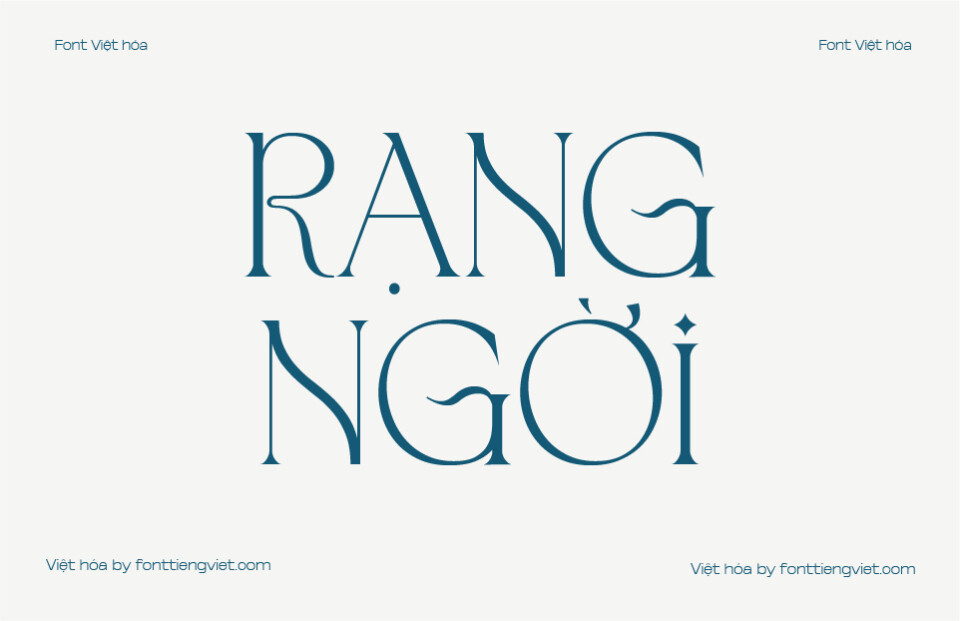
Font Việt hóa 1FTV VIP Vamos
Tải Font Việt hóa 1FTV VIP Vamos – Bộ Font Sang Trọng Cho Thiết Kế Chuyên Nghiệp
Giới thiệu về Font Việt hóa 1FTV VIP Vamos
Trong thế giới đồ họa hiện đại, việc lựa chọn một bộ Font Miễn Phí chất lượng luôn là ưu tiên hàng đầu của các nhà thiết kế. Một trong những cái tên đang gây chú ý gần đây chính là Font Việt hóa 1FTV VIP Vamos. Đây là một bộ font chữ mang phong cách hiện đại, tinh tế và cực kỳ sang trọng, được tinh chỉnh tỉ mỉ để phù hợp với bảng mã tiếng Việt. Với những đường nét thanh mảnh nhưng không kém phần dứt khoát, bộ font này giúp các tác phẩm thiết kế trở nên nổi bật và có chiều sâu hơn. Dù bạn đang làm việc trong lĩnh vực quảng cáo, in ấn hay sáng tạo nội dung số, đây chắc chắn là công cụ không thể thiếu trong bộ sưu tập của mình.
Đặc điểm nổi bật của Font Việt hóa 1FTV VIP Vamos
Bộ font này sở hữu cấu trúc hình học hài hòa, tạo cảm giác dễ nhìn và chuyên nghiệp trên mọi thiết bị hiển thị. Điểm mạnh lớn nhất chính là sự linh hoạt trong ứng dụng, từ các tiêu đề lớn cần sự thu hút đến các đoạn văn bản dài cần sự rõ ràng. Đặc biệt, quá trình Việt hóa đã được thực hiện rất kỹ lưỡng, đảm bảo các dấu câu không bị lỗi hay chồng chéo lên nhau, giữ nguyên được linh hồn và vẻ đẹp nguyên bản của thiết kế gốc.
Tại sao bạn nên chọn Font Việt hóa 1FTV VIP Vamos?
Lý do đầu tiên khiến Font Việt hóa 1FTV VIP Vamos được yêu thích chính là tính thẩm mỹ vượt trội. Trong môi trường học đường hay công sở, việc trình bày văn bản một cách khoa học và đẹp mắt sẽ giúp thông tin được truyền tải hiệu quả hơn. Bộ font này không chỉ dừng lại ở việc hiển thị văn bản mà còn là một phương tiện thể hiện phong cách cá nhân và tư duy thẩm mỹ của người sử dụng. Bên cạnh đó, khả năng tương thích cao với các phần mềm đồ họa phổ biến như Photoshop, Illustrator hay Canva giúp người dùng dễ dàng thao tác mà không gặp bất kỳ trở ngại nào về kỹ thuật.
Ứng dụng thực tế trong học tập và công việc
Đối với các bạn học sinh và sinh viên, bộ font này là lựa chọn tuyệt vời để làm nổi bật các bài thuyết trình PowerPoint hoặc bìa tiểu luận. Vẻ ngoài hiện đại giúp bài làm trông chỉn chu và bắt mắt hơn. Trong khi đó, với các thầy cô giáo hoặc nhân viên văn phòng, việc sử dụng font chữ này cho các thông báo hoặc thiệp mời sự kiện sẽ tạo ra một ấn tượng chuyên nghiệp và lịch sự. Sự đa dạng về độ dày mỏng của các biến thể trong bộ font cũng cho phép người dùng tự do sáng tạo theo ý muốn.
Kết luận về giá trị của bộ font
Tổng kết lại, đây là một tài nguyên thiết kế vô cùng giá trị dành cho cộng đồng sáng tạo tại Việt Nam. Sự kết hợp giữa vẻ đẹp quốc tế và sự tinh chỉnh thuần Việt đã tạo nên một sản phẩm hoàn hảo. Nếu bạn đang tìm kiếm một giải pháp để nâng tầm chất lượng hình ảnh cho dự án cá nhân hay tổ chức, hãy truy cập ngay vào Font Miễn Phí, Font Việt Hóa, Font Việt hóa 1FTV VIP Vamos để trải nghiệm sự khác biệt. Hy vọng rằng bộ font này sẽ trở thành người bạn đồng hành tin cậy, giúp bạn khơi nguồn cảm hứng và gặt hái được nhiều thành công trong con đường sáng tạo nội dung sắp tới của mình.